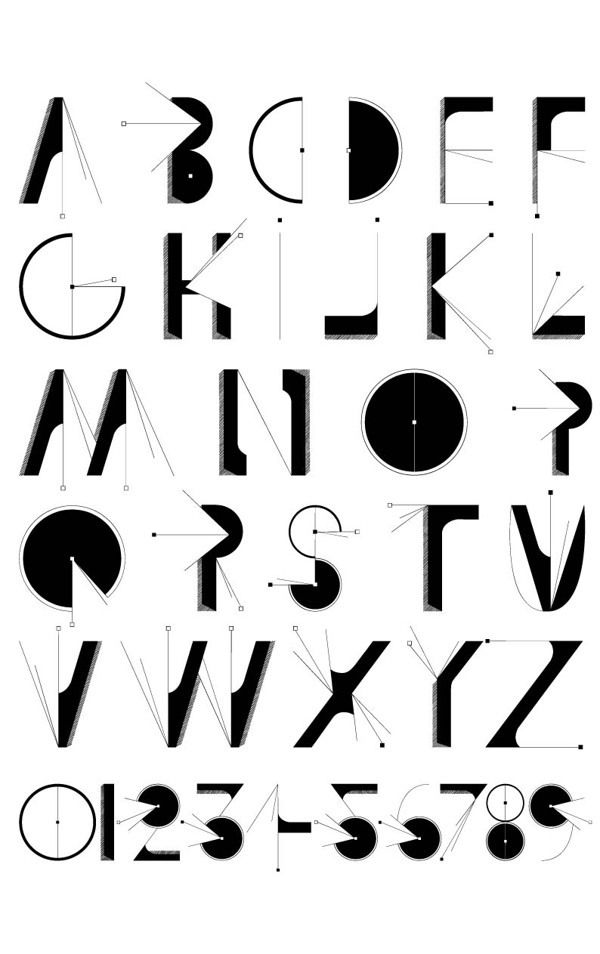
6 уникальных геометрических шрифтов в вашу копилку
От автора: типографика одна из самых динамичных и постоянно меняющихся областей дизайна, сильно влияющая на общее ощущение от вашего сайта. И действительно, типографика позволяет нам пробудить в пользователе те мысли и чувства, которые заложены в подобранном шрифте.
Как правило, и на сайтах, и в мобильных приложениях лучше смотрятся шрифты без засечек (sans-serif) – засечки лучше смотрятся на бумаге. Свойства шрифта без засечек делают его идеальным для плоского дизайна, сохраняя при этом высокую читабельность текста.
Но существует намного больше категорий, нежели просто с засечками и без. Вторые подразделяются на 4 категории: Гуманистические (humanist), Гротескные (grotesque), Нео-гротескные (Neo-grotesque) и Геометрические (Geomitric).
В этой статье мы изучим работы дизайнеров, которые на самом деле знают, как хорошо использовать геометрические шрифты – и, как бонус, пополним свою копилку отличными шрифтами.
Узнать подробнееЧто мы имеем в виду, говоря «Геометрический шрифт»?
Из названия понятно, что они состоят из простых геометрических фигур, как круг и квадрат. Геометрические шрифты обычно используются в заголовках печатных изданий, но также и подходят для мобильных и настольных дизайнерских проектов.
Эксперты проследили рост геометрических шрифтов в школе Bauhaus, немецкая школа искусств, работавшая с 1919 по 1933. И совсем не совпадение, что «Futura» один из самых известных геометрических шрифтов, созданный в 1927 Паулем Реннером, дизайнером, на которого сильно повлияло течение Баухаус.
Одним из ключевых принципов учений Баухаус было максимальная фокусировка на простоте и функциональности, а не на украшениях. Futura стильная комбинация точных металлических форм и утонченной элегантности.
Геометрические шрифты на практике
Ниже представлено пара примеров того, как с помощью геометрических шрифтов можно добиться хороших результатов.
Jova это строительная фирма, специализирующаяся на ремонте домов и магазинов.
На их сайте реализовано нестандартное меню, основанное на сетке, оно очень простое, профессиональное и достаточно изысканное, а также отлично сочетается с изображениями бренда.
Дизайнеры задумали использовать геометрический шрифт: я думаю это правильное решение, линейность тонкого шрифта усиливает общие ощущения от дизайна.
Второй пример – «Le Parc Records», музыкальный лейбл. Сайт создает вокруг себя темный ореол современности, могущества, все это благодаря удачным фоновым изображениям и отлично подобранному шрифту.
Фото само по себе выглядит круто, но шрифт помогает связать все вместе, хоть он и немного странный. Шрифт геометрический, без засечек, но с некоторыми вставками на отдельных буквах типа «О» и «Х».
Этот пример доказывает, что геометрические шрифты могут быть не только четкими, элегантными, как Jova, но и более крутыми, «острыми», как Le Parc.
Последний пример – телевизионный канал в США «Comedy Central». Несколько лет назад Comedy Central прошел процесс ребрендинга, представив новый логотип и дизайн.
Ребрендингом занималось «theLab», креативное агентство, они решили использовать геометрический шрифт «Brandon Grotesque», чтобы подчеркнуть доверие и возраст компании.
Шрифт всегда в верхнем регистре, даже в логотипе, как, в принципе, и в остальном тексте на сайте. Такой подход вызывает чувство элегантности и знания своего дела, в то же время изображения добавляют нотку юмора, которое отличает Comedy Central от остальных.
Геометрические шрифты в вашу копилку
Теперь, когда мы посмотрели на то, как могут быть использованы геометрические шрифты, настало время поискать самые лучшие из них для себя.
Attitude
Дизайнер шрифта, Emil Kozole говорит, что создание было вдохновлено японской и американской культурой начала 90-ых годов. Дизайнер определенно экспериментировал с буквами и формами.
В результате получилось очень похоже на «Le Parc Records».
Узнать подробнееШрифт имеет 7 разных версий: “regular”, “inline”, “3d”, “sliced”, “soldier”, “drunk” and “wasted”. Все версии, кроме «inline» имеют по 2 стиля: “regular” and “alternate”. Шрифт «Attitude» минималистичный, хорошо подходит для постеров, дизайнерской одежды, журналов и обложек дисков, и уж тем более он подходит для заголовков. Загрузить можно здесь.
Biko
Biko геометрический шрифт без засечек от Marco Ugolini для сайта Monofonts. Название это дань уважения Стиву Бико, южно африканскому активисту, борцу с Апартеидом.
В Biko достаточно дружелюбные, но точные, сильные буквы, из-за чего он отлично смотрится на мобильных приложениях, в качестве основного текста и в логотипах. Доступен в 4 различных видах: light, regular, bold and black. Если вы хотите использовать его для себя, бесплатную версию можно загрузить здесь.
HK Nova
HK Nova ™ Typeface разработан Hanken Design Co. Геометрические формы Century Gothic и Futura могут оказать большое влияние на этот шрифт. Этот удобный для использования шрифт поставляется с различными стилями, которые вы можете комбинировать, чтобы получить наилучшие результаты для ваших дизайнов.
Geometos
Geometos — это дизайн без засечек, созданный Дипаком Догра.Этот шрифт бесплатен для личного использования. В Geometos есть символы, знаки препинания и числа.